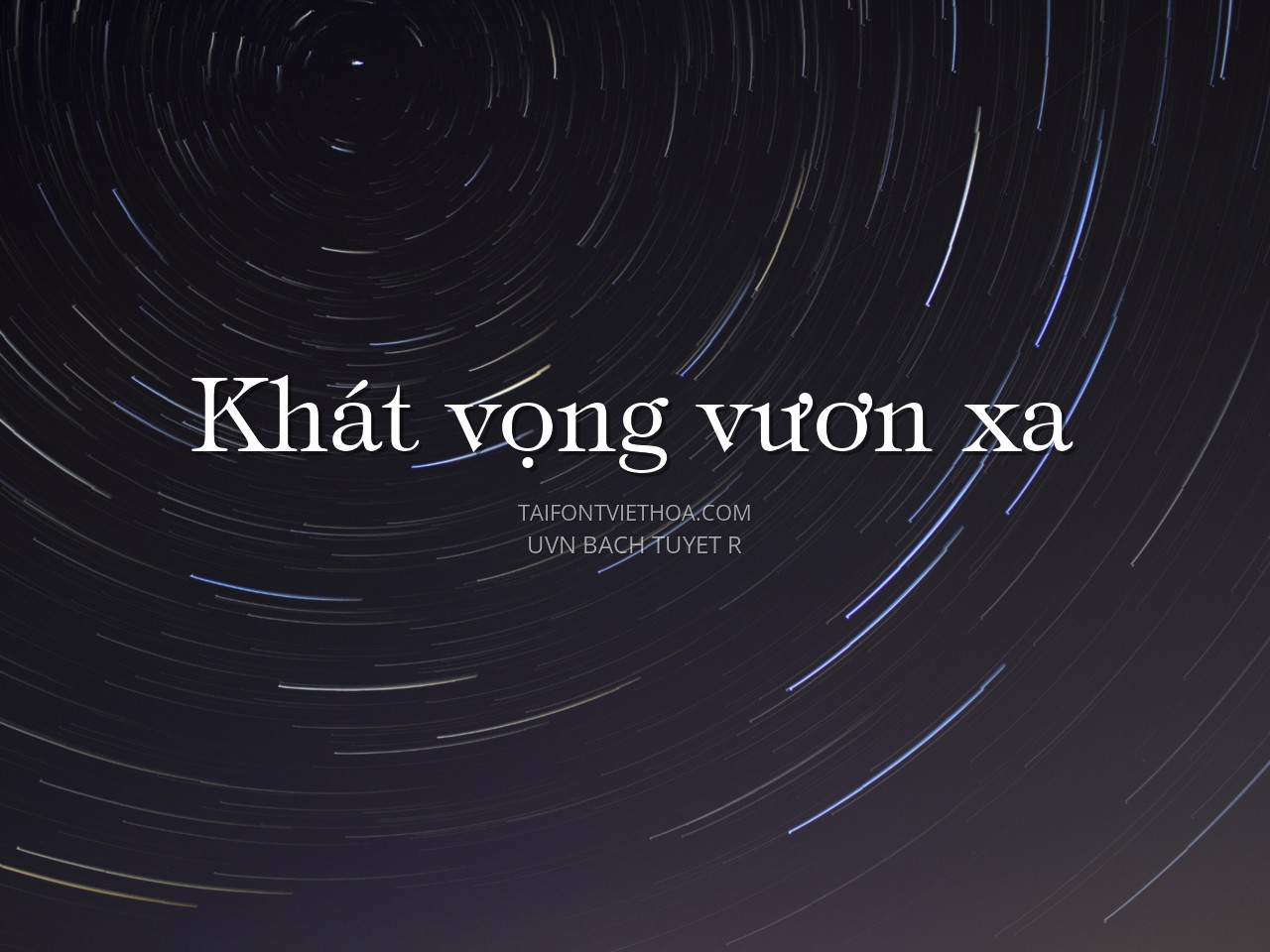
Giới thiệu về font UVN Bach Tuyet
UVN Bach Tuyet là một kiểu chữ serif mềm mại mang hơi thở lãng mạn, cổ điển nhưng thanh lịch. Với tên gọi gợi cảm giác tinh khiết và thuần túy như tuyết trắng, font tạo ấn tượng thị giác nhẹ nhàng và sang trọng. Thiết kế này thích hợp với các ấn phẩm cần truyền tải sự tinh tế, nữ tính hoặc mang đậm chất văn học. Font được sưu tầm và chia sẻ bởi thành viên của Font Chuẩn và đã được taifontviethoa.com chọn lọc, thử nghiệm trong các dự án thiết kế sáng tạo, truyền thông văn hóa và ấn phẩm in ấn chất lượng cao.
Đặc điểm thiết kế và ứng dụng của UVN Bach Tuyet
Font sở hữu các đường nét cong mượt, chân chữ nhẹ, bố cục thanh thoát mang tính nghệ thuật cao. Cấu trúc rõ ràng giúp UVN Bach Tuyet vẫn đảm bảo khả năng đọc tốt ở kích thước nhỏ. Font này rất phù hợp cho tiêu đề sách, bìa truyện, tạp chí, thư mời, hoặc bao bì sản phẩm cao cấp.
Ứng dụng lý tưởng trong ngành thời trang, mỹ phẩm, thiệp cưới, ấn phẩm nữ tính, sản phẩm dành cho trẻ em hoặc các dự án văn hóa truyền thống mang hơi hướng cổ điển và nhẹ nhàng.